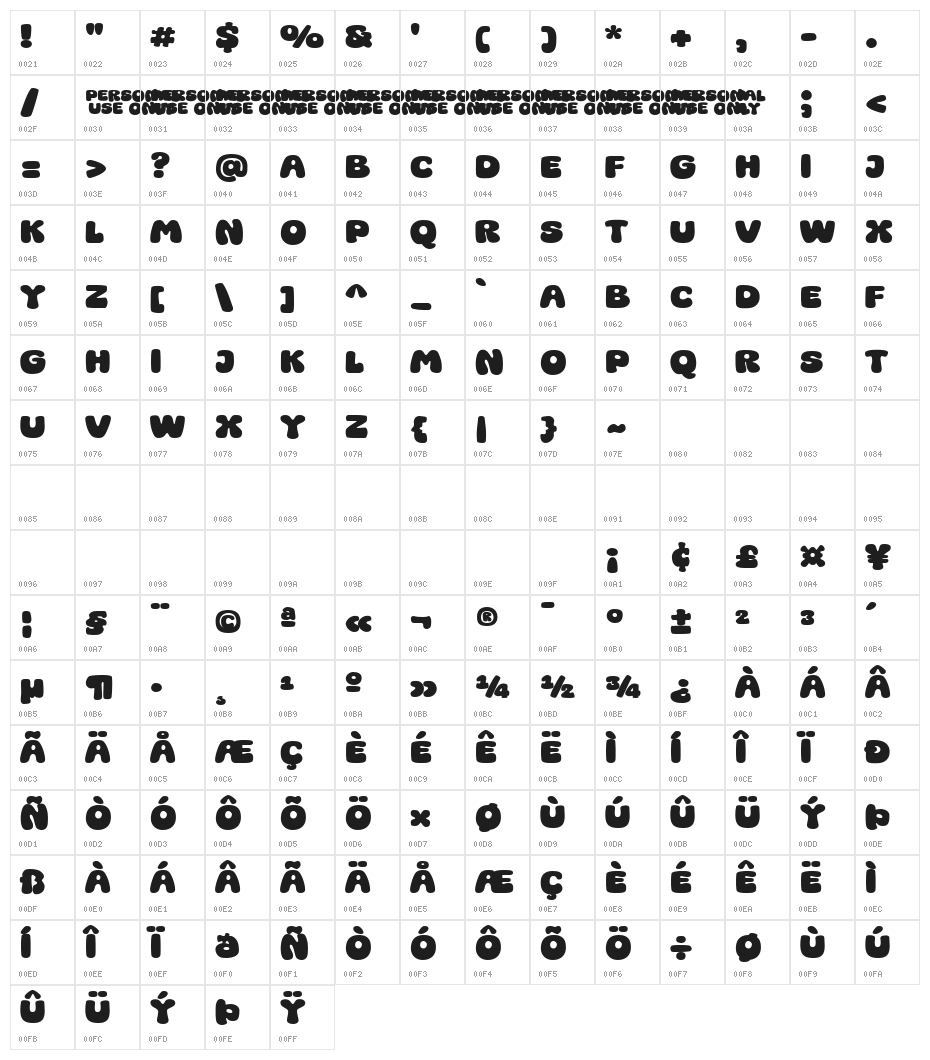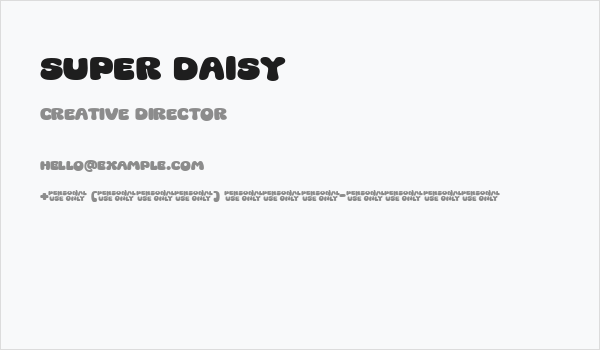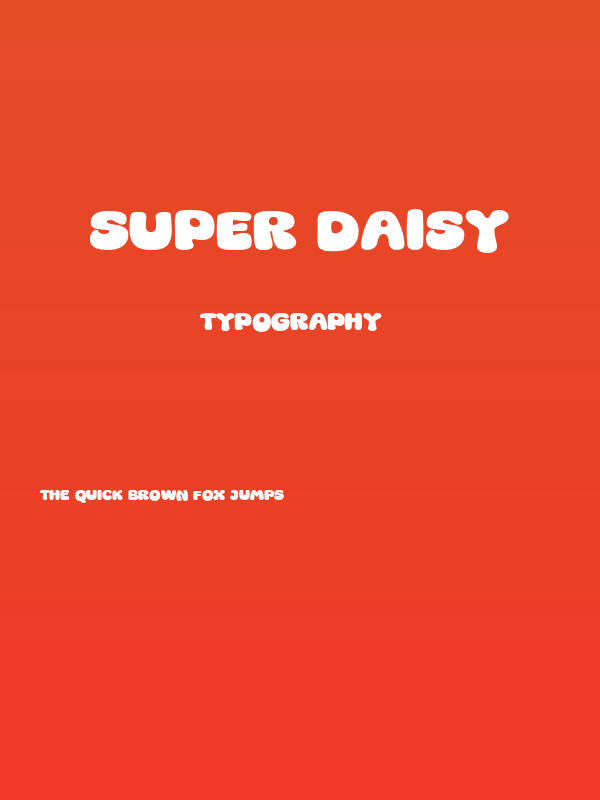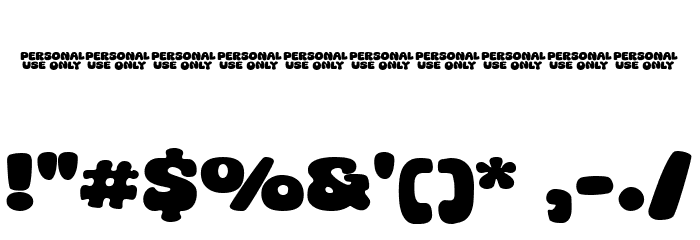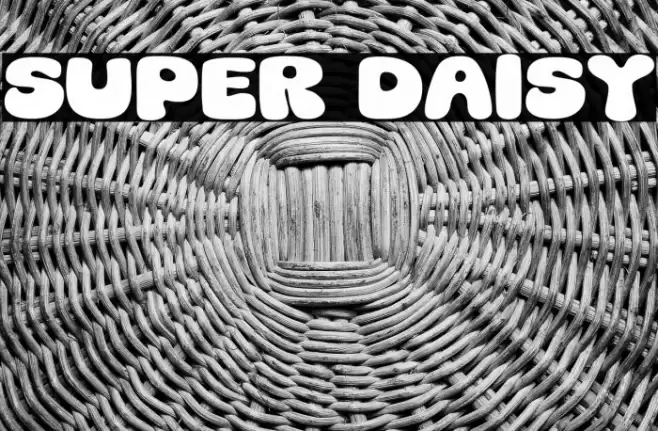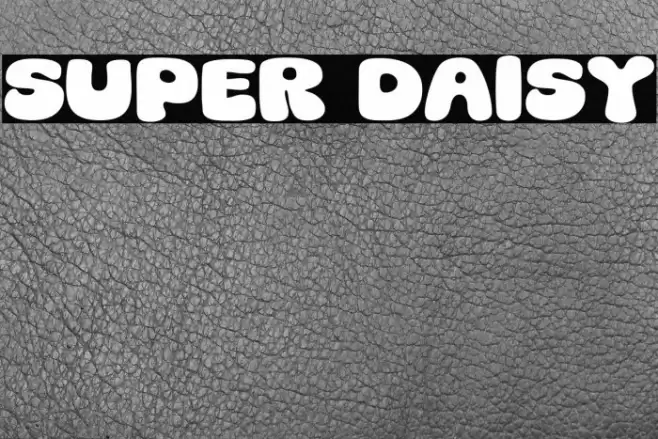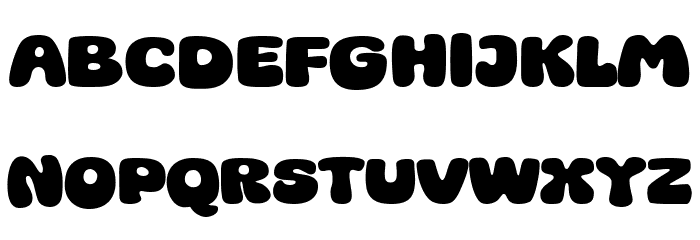
Super Daisy Font
| النمط العام | Playful, Retro |
| مشاريع مقترحة | Great for children's books, playful branding, party invitations, and retro-themed posters. |